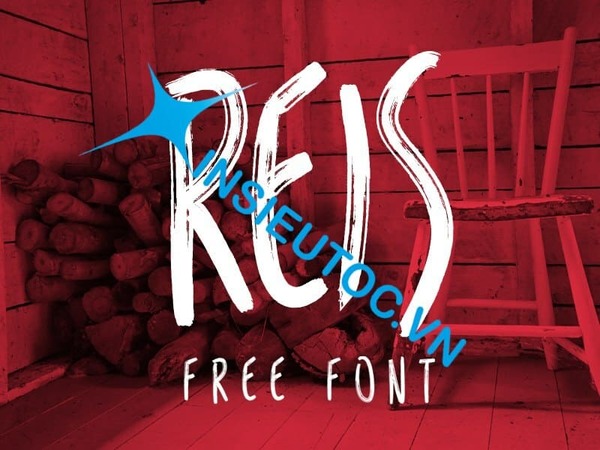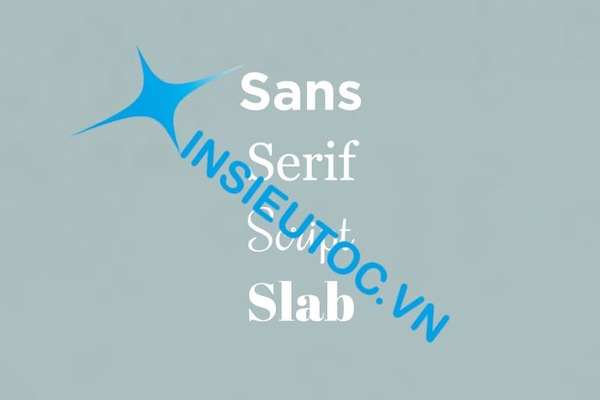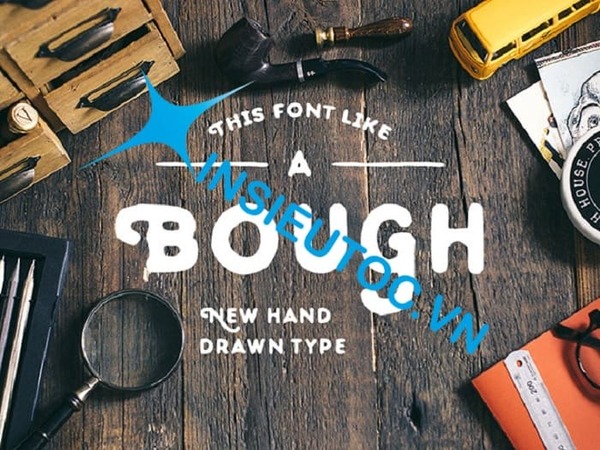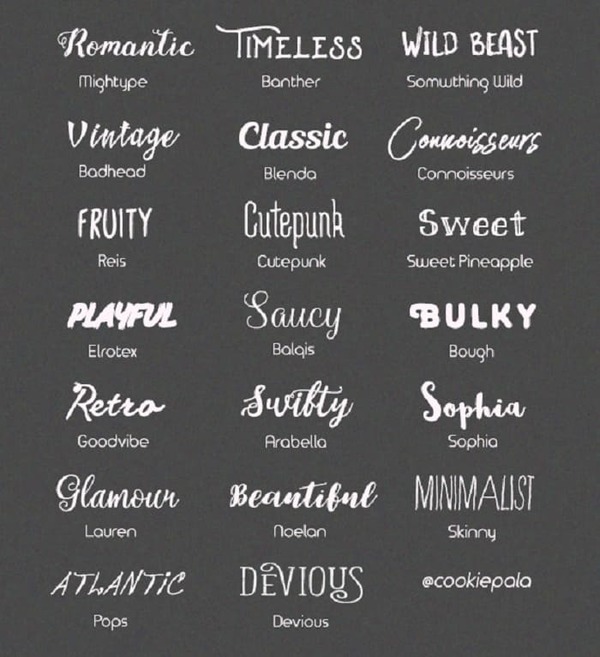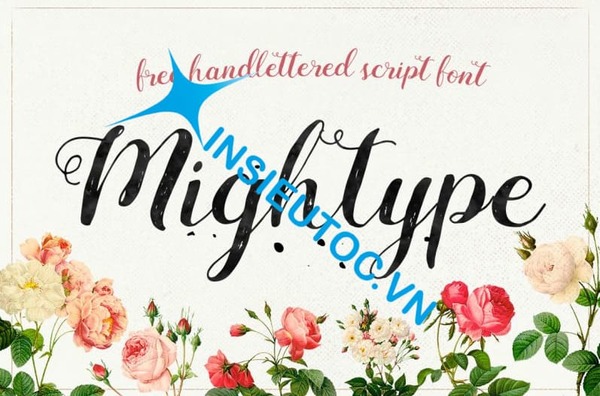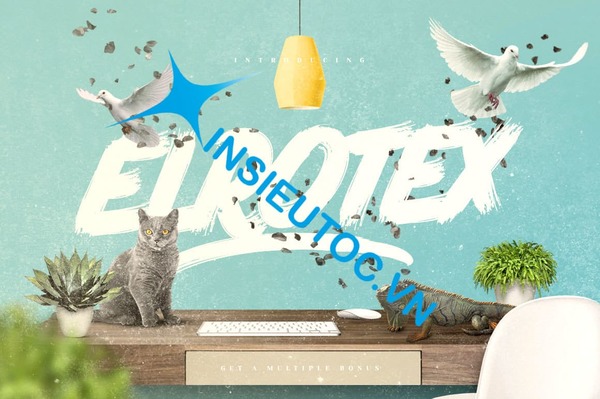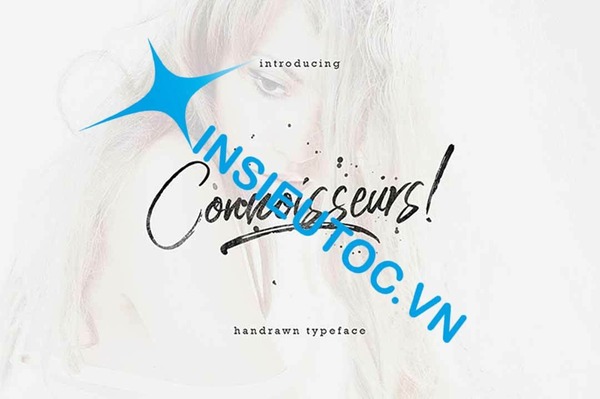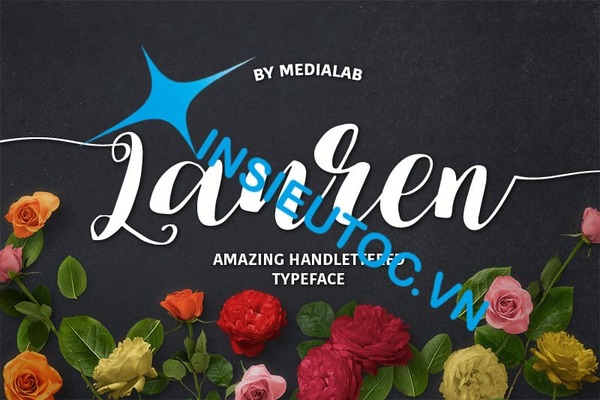
Top font chữ thiết kế tờ rơi ấn tượng được nhiều người sử dụng
Font chữ thiết kế tờ rơi đẹp sao cho phù hợp ý tưởng và phong cách thiết kế luôn khiến các designer đau đầu mỗi lần thực hiện dự án. Tham khảo ngay top font chữ thiết kế tờ rơi đẹp trong bài viết sau để tìm được cho mình kiểu chữ đẹp mắt, ấn tượng và thu hút khách hàng nhất cho thiết kế tờ rơi quảng cáo của bạn.
Font chữ nào khi thiết kế tờ rơi thu hút khách hàng?
1. 14 loại font chữ đẹp dùng để thiết kế tờ rơi
14 font chữ viết tay bắt mắt dành cho thiết kế tờ rơi
Font chữ GARAMOND
Xuất phát từ Paris thế kỷ 16. Font này dễ đọc nên đây là lựa chọn hoàn hảo dùng để thiết kế tờ rơi và các mẫu in ấn nhỏ như catalogue, poster,…
Font chữ GARAMOND
Font chữ FRANKLIN GOTHIC
Font chữ FRANKLIN GOTHIC đơn giản, dễ đọc. Kiểu chữ này gây ấn tượng bởi độ rộng của mỗi ký tự. Do đó tạo ra hiệu ứng như bị đè bẹp khi nhìn. Các mẫu in tờ rơi sử dụng kiểu chữ này dễ gây ấn tượng và thu hút người nhìn.
Font chữ FRANKLIN GOTHIC
Font chữ  BODONI
Kiểu chữ BODONI thể hiện sự tương phản giữa các nét dày và mỏng. Từ đó nó trở thành kiểu chữ tuyệt vời trên các tờ rơi quảng cáo sự kiện nghệ thuật như quán trà, quán cafe mang phong cách cổ điển.
Font chữ BODONI nghệ thuật
Font chữ Decoration
Là sự pha trộn giữa 3 font chữ serif, sans serif và scripts. Thể hiện sự độc đáo trong thiết kế tờ rơi.
Font chữ Decoration
Font chữ Sans Serif
Sans Serif là kiểu chữ không chân được nhiều nhà thiết kế sử dụng cả trong thiết kế tờ rơi cũng như trong in những mẫu banner đẹp vì mang phong cách hiện đại và rõ ràng. Helvetica và Futura là 2 kiểu chữ “biểu tượng” cho Sans Serif. San Serif được dùng để thiết kế logo, poster, portfolio, font chữ thể thao,… .
Font chữ Sans Serif hiện đại
Font chữ Serif
font chữ thiết kế tờ rơi đẹp có chân, mang hơi hướng cổ điển và bắt đầu thịnh hành từ thế kỷ XV. Các kiểu chữ phân loại khác nhau như: Old Style, Slab serif, Transitional, Gardener, Classical, Neo-classical, Increment, Typewriter,… Font chữ Serif được dùng trong thiết kế tờ rơi, banner, logo, poster, bìa sách,…
Font chữ Serif
Font chữ Mightype
Font chữ này được thiết kế bởi AF Studio. Font chữ Mightype sử dụng cho thiết kế tờ rơi shop quần áo, quán cafe và cửa hàng bởi sự đơn giản và hoàn hảo mà nó thể hiện.
Font chữ Mightype thanh thoát
Font chữ Something Wild
Something Wild là một trong những Font chữ thiết kế tờ rơi đẹp được sáng tạo bởi team MediaLab. Với phong cách hoang dã và nguyên sơ, font chữ này thường được dùng khi thiết kế tờ rơi quán cafe hay mẫu thiết kế có nền đen.
Font chữ Something Wild hoang dã
Font chữ Badhead
Font chữ này được tạo ra bởi Ianmikraz Studio. Font chữ Badhead mang theo nét cổ điển và thanh lịch nên được sử dụng khi thiết kế thiệp chúc mừng, thiết kế thương hiệu,,…
Font chữ Badhead
Font chữ Elrotex
Font chữ này mang tính sáng tạo và mới mẻ cho các thiết kế, được sáng tạo bởi Maulana Creative. Elrotex thích hợp cho thiết kế sự kiện ngoài trời hay hội chợ triển lãm.
Font chữ Elrotex
Font chữ Connoisseurs
Connoisseurs là một font chữ viết tay thanh lịch có nguồn gốc từ Pixelbuddha. Font chữ này thích hợp cho thiết kế poster, logo, thiệp chúc mừng, thiết kế studio,…
Font chữ Connoisseurs lãng mạn
Font chữ Reis
Font chữ thiết kế tờ rơi đẹp này được sáng tạo bởi Marcelo Reis Melo. Các nét không đều nhau tạo nên sự duyên dáng mới lạ, thời trang. Rất thích hợp thiết kế quán trà sữa, quán ăn, nhà hàng,…
Font chữ Reis
Font chữ Lauren
Font chữ Lauren có phong cách chữ thư pháp nhẹ nhàng nhưng cũng không kém phần mạnh mẽ. Đồng thời font chữ cũng kèm theo sự thay thế phong cách thông qua các tính năng OpenType của nó. Font chữ này được ưa chuộng thiết kế thiệp mời, thiệp cưới.
Font chữ Lauren
Font chữ Bough
Bough là font chữ viết tay được sáng tạo bởi Pavel Korzhenko. Kiểu chữ thông thường trên nền phong cách cổ điển tạo cảm giác mới lạ, nhẹ nhàng. Font chữ thích hợp thiết kế tờ rơi ca nhạc, cà phê.
Font chữ Bough
2. Quy tắc chọn font chữ trong thiết kế tờ rơi
Ngoài việc lựa chọn font chữ khi thiết kế tờ rơi, các designer cần phải lưu ý thêm các yếu tố như: kích thước in tờ rơi, màu chữ, màu nền,… để ý tưởng và phong cách được hòa hợp:
Lựa chọn font chữ thiết kế tờ rơi không khó, chỉ cần nắm được căn bản và phối hợp hài hòa các yếu tố với nhau sẽ tạo ra những mẫu thiết kế tờ rơi sáng tạo. Hy vọng với những chia sẻ trên, các bạn sẽ tìm được Font chữ thiết kế tờ rơi đẹp phù hợp với sản phẩm của mình.